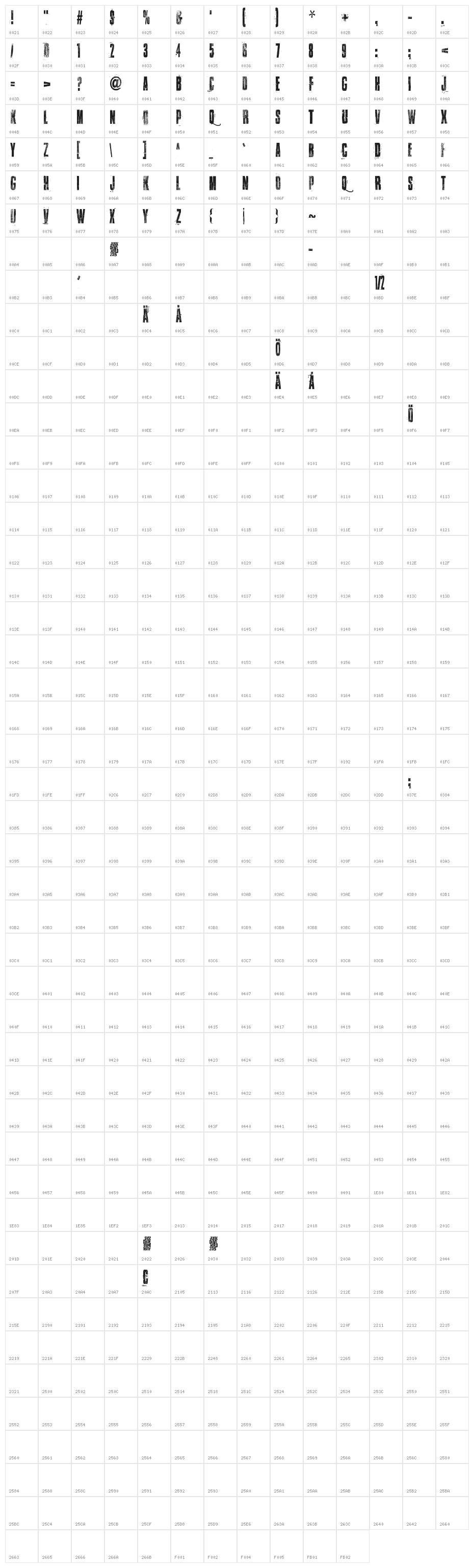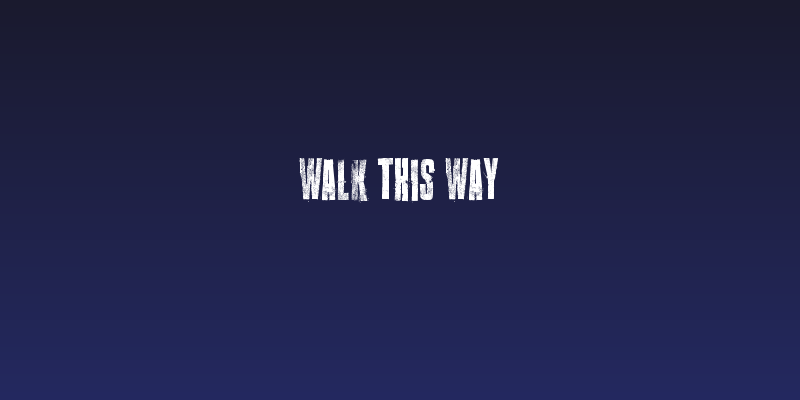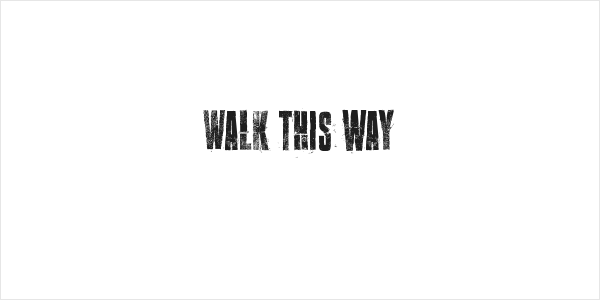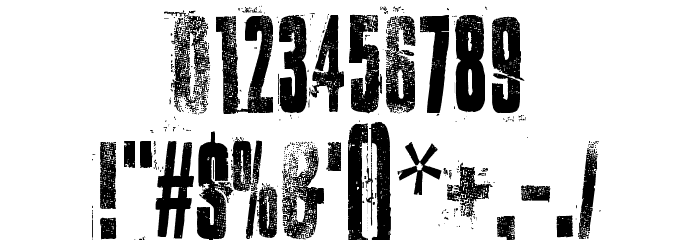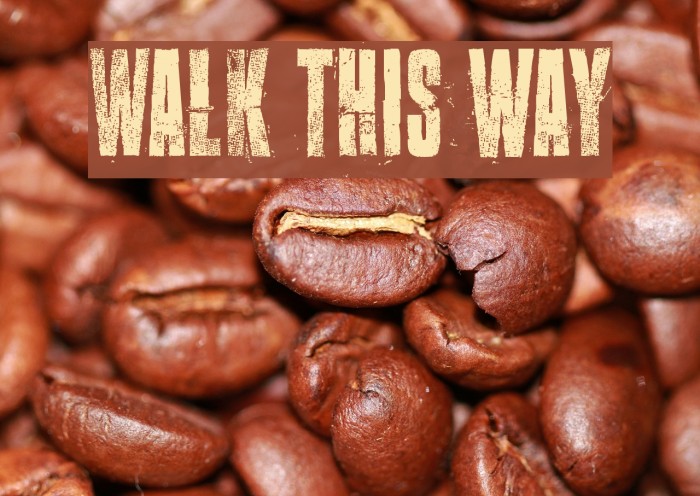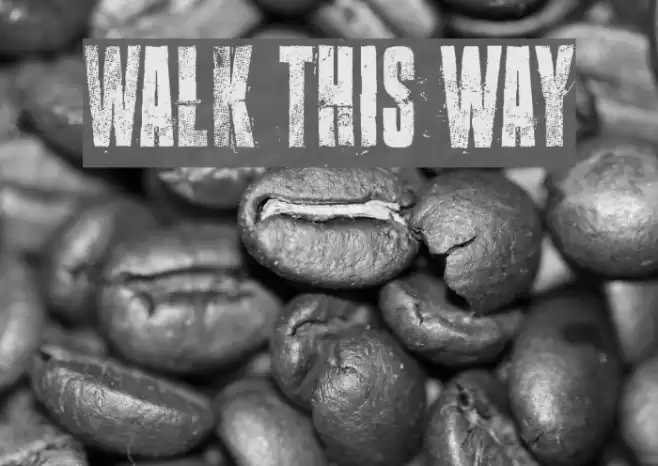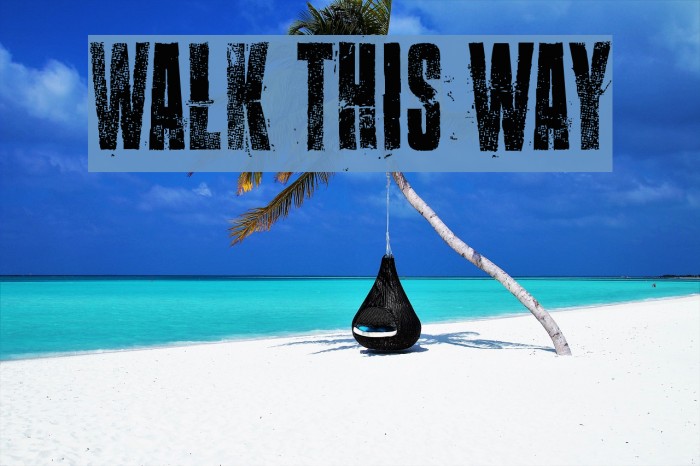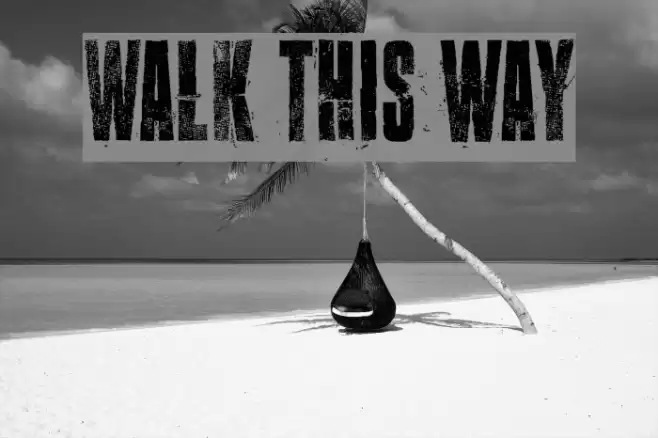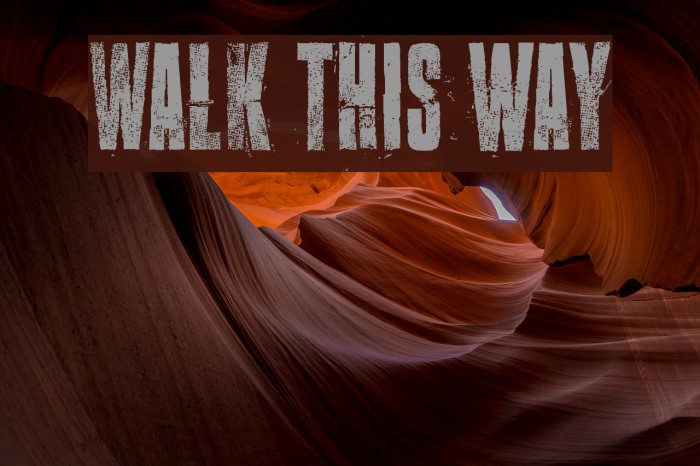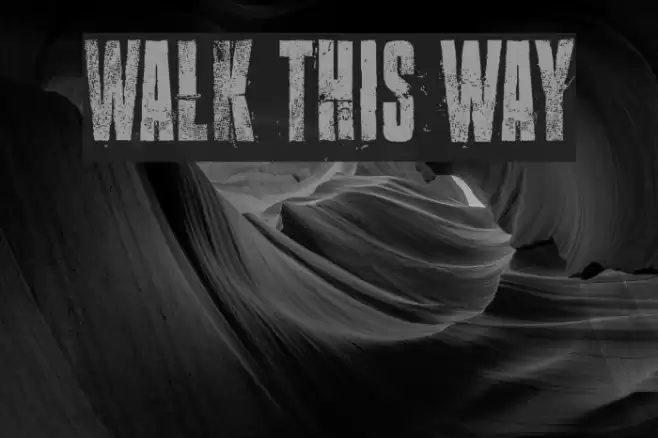
Walk this way Font
✎ Distorted Eroded
| Categorie | Distorted Eroded |
| Progetti proposti | Ideal for posters, album covers, branding for rugged products, or any design needing a vintage or industrial touch. |